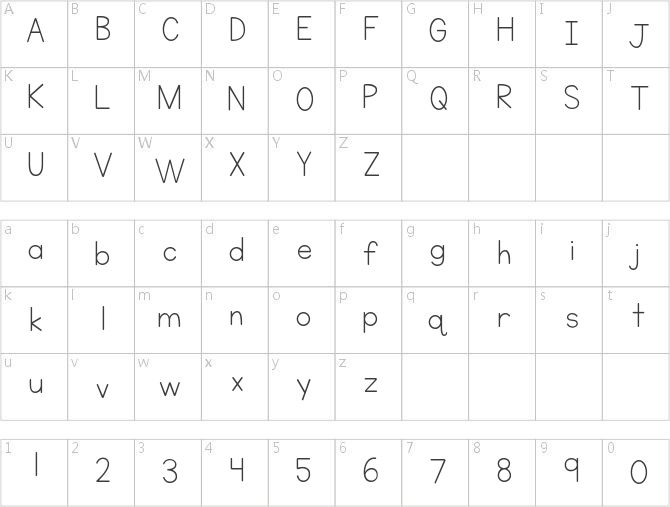
KG Neatly Printed Spaced 詳情頁
KG Neatly Printed Spaced字體字庫是一款讓人賞心悅目、百看不厭的英文字體,適合各類廣告和產(chǎn)品包裝設(shè)計應(yīng)用,字體大小0.03MB,格式為ttf字體,上傳用戶是yinjun,作者/版權(quán)方為未知